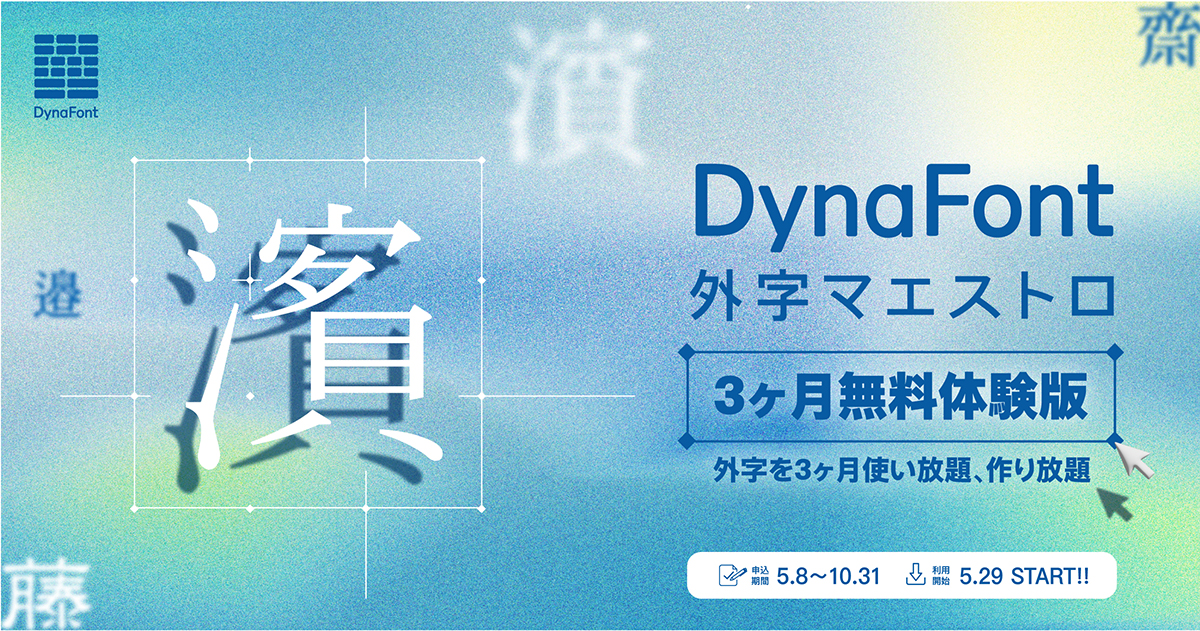
パソコンで表示できない「外字」を3ヶ月使い放題、作り放題!「DynaFont外字マエストロ3ヶ月無料体験版」を5月29日から提供開始
「DynaFont外字マエストロ」は4,718文字の外字に183種類の案内用図記号(ピクトグラム)を収録した合計外字4,901文字対応のダイナフォント19書体を使用でき、外字も作成可能な常に最新の外字フォント環境が行き渡る外字フォント年間ライセンス製品。
パソコン上で正しく変換・表示できないトラブルが懸念される「外字」
外字とは通常のPC標準書体などに搭載されていない文字で、テキスト入力の際に変換しても表示できない文字。例えばワタナベ姓の人が自分のナベという漢字をPCなどで入力しようとした時に正しい字形の漢字が表示されず文字化けしてしまうことがありますが、その漢字こそ外字に該当。
また外字は人名や地名に多くありますが、その他にも枠付き文字や単位記号、省略文字、シンボルマークなども含まれている
宛名印刷から、名簿作成、ビジネス文書、各種案内状、賞状・証書、各種書類、ECサイト、管理システムなどに至るまで、正しい形の文字を必要とする状況において外字は大変な懸案事項といる。
DynaFont外字マエストロなら「ピクトグラム」を含む4,901文字の外字が使い放題!
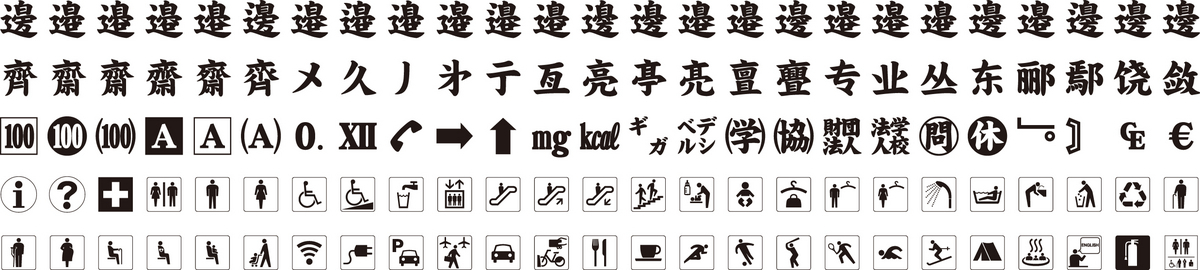
法務省指定となる人名用漢字を全て網羅し、各自治体で採用されている人名外字など使用頻度の高い人名外字3,296文字を厳選して収録しており、名簿作成での正しい人名表記や、はがきソフトなどでの宛名書きなど様々な場面で使用できる。
さらにBiblos記号外字1,395文字、貨幣外字27文字に加え、日本で開催される国際的なイベントやインバウンド需要を受けて更に需要が高まるピクトグラム(案内用図記号)183種類も収録し、合計4,901文字の外字を収録している。
DynaFont外字マエストロなら外字対応「超極太楷書体」を新たに収録した厳選19書体が使い放題!
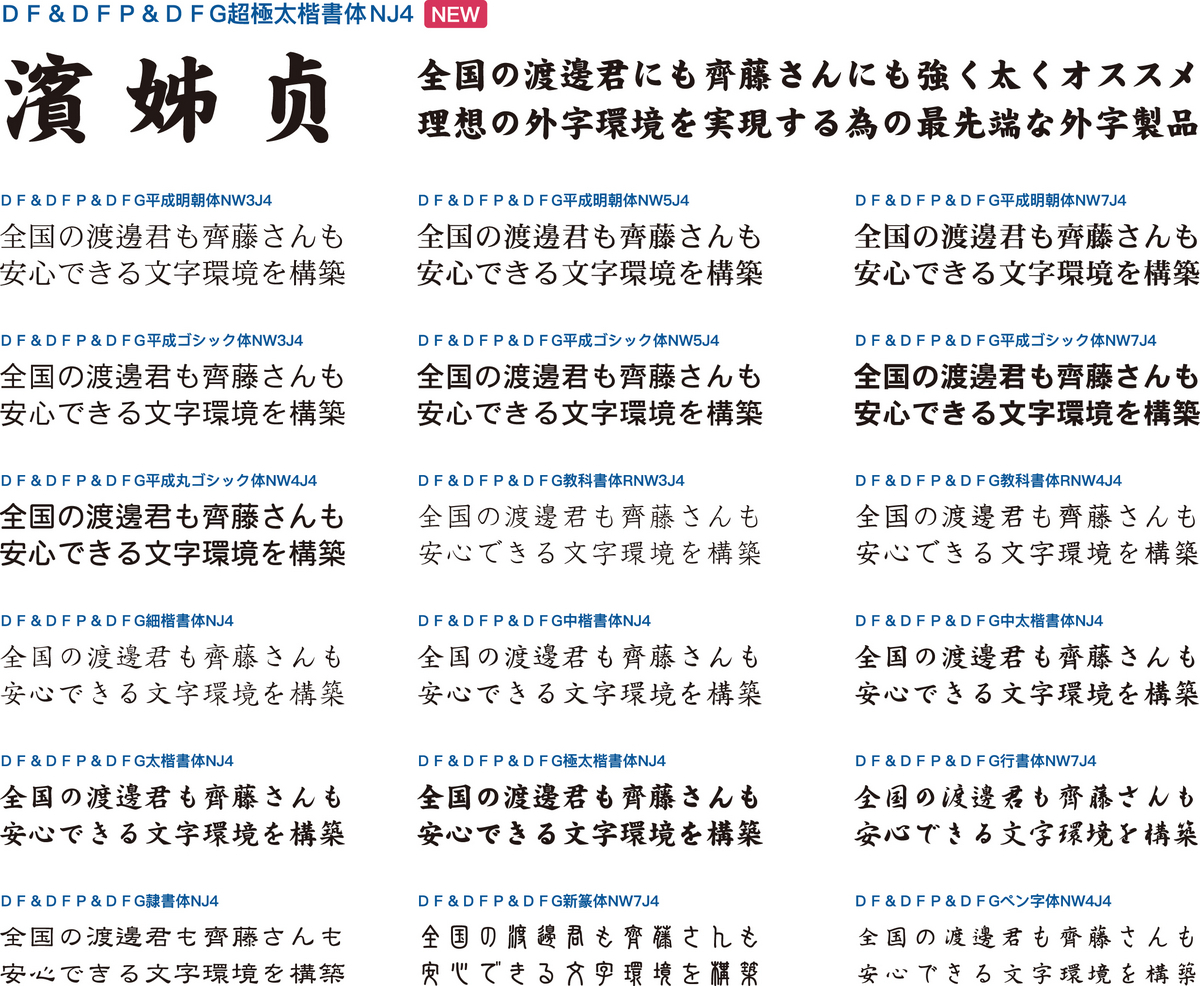
「DynaFont外字マエストロ」ではダイナコムウェアのこれまでの外字対応フォント製品に加え、新たに「超極太楷書体」を外字対応書体の新書体として収録し、外字対応19書体が使用できる。
さらに今後も最新書体および最新外字が随時追加されていき、常に最新の外字フォント環境が行き渡る。
DynaFont外字マエストロなら足りない外字も「外字作成ツール」で簡単、キレイに作り放題!
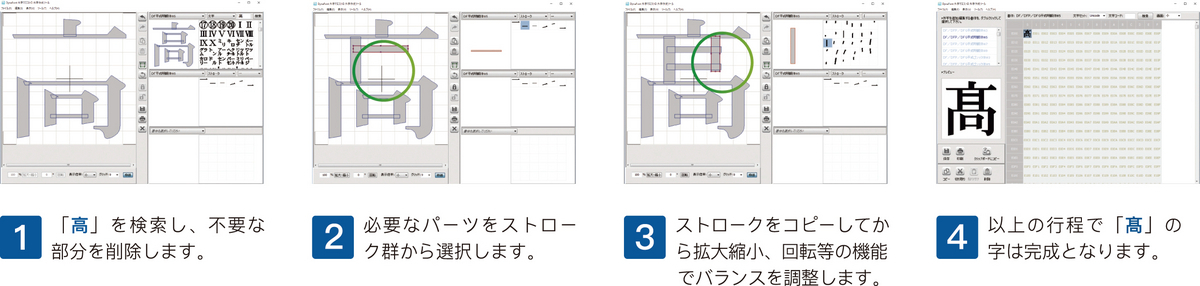
Windows OS環境では「DynaFont外字マエストロ」に収録されていない特殊な文字を使用したい場合、『外字作成ツール』を使用して簡単な操作で綺麗な外字が作成できる。
「DynaFont外字マエストロ」収録19書体の既存の漢字から一筆(ストローク)単位でパーツを取り出すことができ、また取り出したパーツを他の漢字や一筆と組み合わせる事で迅速かつ簡単に外字が作成できまる。
約300種類におよぶ豊富なストロークを搭載しており、ストローク同士の組み合わせや他の漢字の一部と組み合わせることで無限に近い数の外字を作成できる。